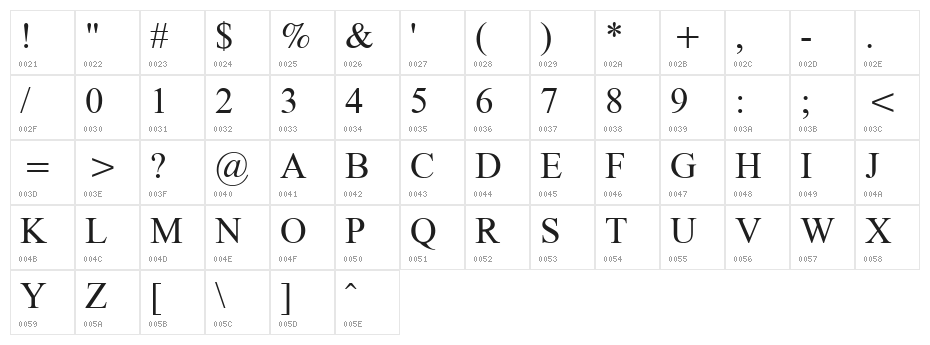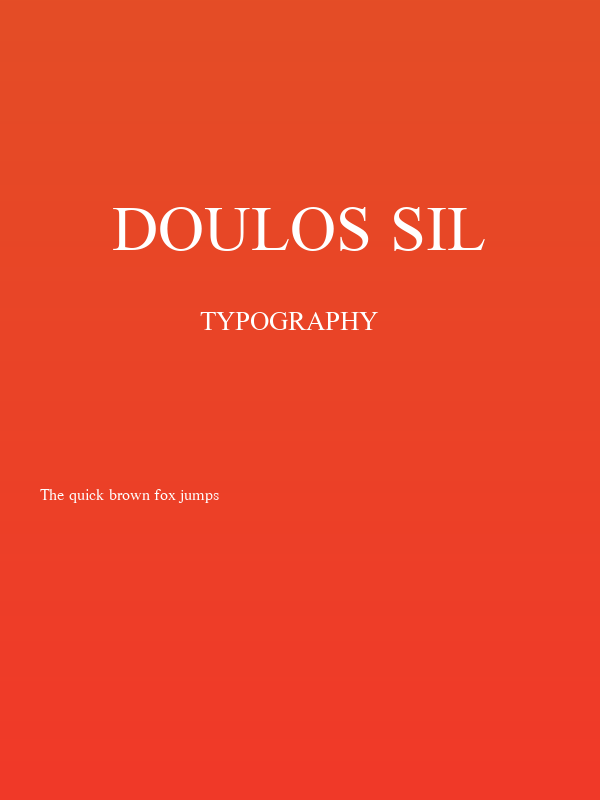
Doulos SIL Font
✎ Serif
| Categorie | Serif |
| Caso d'uso | Body text, Headlines, Formal documents |
| Progetti proposti | This font is perfect for projects that require a touch of elegance and tradition, such as book typesetting, formal invitations, academic publications, and sophisticated branding. |